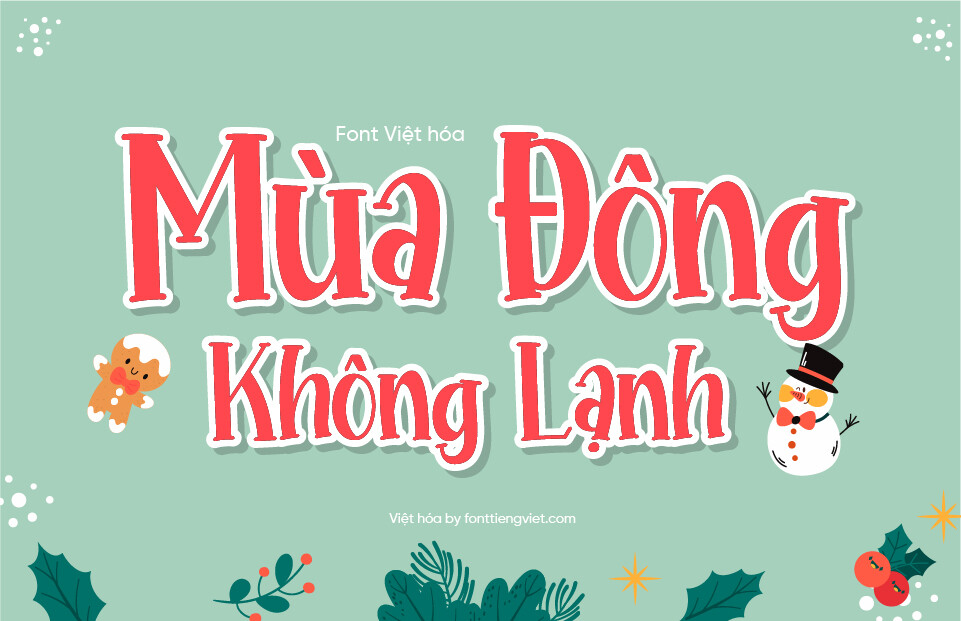
Font Việt hóa 1FTV Hopeful Christmas Solid – Giáng sinh cực đẹp cho thiết kế
Giới thiệu về Font Việt hóa 1FTV Hopeful Christmas Solid – Giáng sinh
Mùa lễ hội cuối năm luôn là thời điểm tuyệt vời để các bạn học sinh và thầy cô cùng nhau trang trí lớp học hay làm những tấm thiệp chúc mừng ý nghĩa. Để tạo nên không khí ấm áp, việc lựa chọn Font Chữ phù hợp là vô cùng quan trọng. Font Việt hóa 1FTV Hopeful Christmas Solid – Giáng sinh chính là giải pháp hoàn hảo mang lại vẻ đẹp hiện đại nhưng không kém phần gần gũi cho mọi sản phẩm thiết kế đồ họa trong dịp Noel này.
Đặc điểm nổi bật của bộ font chữ
Bộ font này sở hữu những nét vẽ dày dặn, chắc chắn nhưng vẫn giữ được sự mềm mại cần thiết. 1FTV Hopeful Christmas Solid được thiết kế theo phong cách thủ công, giúp các câu chúc trở nên sinh động và có hồn hơn. Đặc biệt, phiên bản Việt hóa đã được tối ưu hóa hoàn toàn về dấu câu, giúp người dùng dễ dàng gõ tiếng Việt mà không lo lỗi hiển thị. Đây là lựa chọn lý tưởng cho các bạn học sinh muốn tự tay thiết kế nhãn vở, thời khóa biểu hay các băng rôn chào mừng Giáng sinh tại trường.
Cách ứng dụng Font Việt hóa 1FTV Hopeful Christmas Solid – Giáng sinh hiệu quả
Để khai thác tối đa vẻ đẹp của font, bạn nên kết hợp với các tông màu truyền thống như đỏ, xanh lá cây hoặc vàng kim. Font Việt hóa 1FTV Hopeful Christmas Solid – Giáng sinh rất phù hợp để làm tiêu đề cho các bài thuyết trình PowerPoint về chủ đề mùa đông. Bên cạnh đó, các thầy cô có thể sử dụng font này để thiết kế phiếu khen hoặc thư mời tham dự văn nghệ cuối năm, tạo sự hứng thú và niềm vui cho các em học sinh.